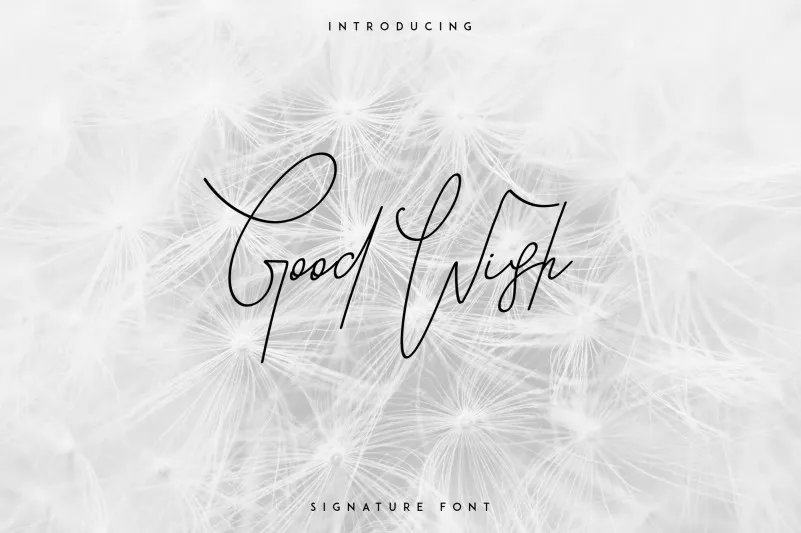
Good Wish Signature Font – Fonte Grátis
Good Wish Signature Font
A ‘Good Wish Signature Font’ é uma escolha perfeita para quem busca personalidade na hora de assinar. Desenvolvida pelo designer vp_creative_shop, essa fonte é versátil e oferece estilos tanto regular quanto itálico, garantindo que seu nome seja notado por todos os seus contatos e clientes. Perfumada com suporte a várias línguas, esta fonte é perfeita para assinaturas em grande ou pequeno tamanho. Seja um registro de negócios robusto ou uma assinatura personalizada mais íntima, Good Wish Signature Font se encaixa perfeitamente. Sua facilidade de uso e a variedade de estilos tornam essa fonte uma opção indispensável para quem busca destaque em qualquer projeto de identificação visual.